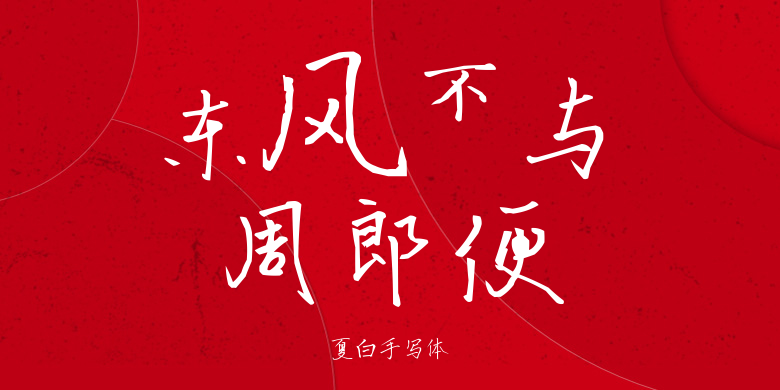
夏白手写体
夏白手写体,这款字体结构工整、笔画清晰,兼顾美观与易读性,适用于标题、正文、海报、包装、LOGO 等多种场景。字形优雅稳定,风格百搭耐看,适配日常排版与创意设计,让文字呈现更舒适、更具质感。夏白手写体一笔一画,皆是细节,以均衡的比例、流畅的线条打造舒适视觉体验,字形端正大气,风格简约现代。无论是商业设计、品牌宣传还是日常排版,都能轻松驾驭,让文字更有格调与力量。夏白手写体字体下载。